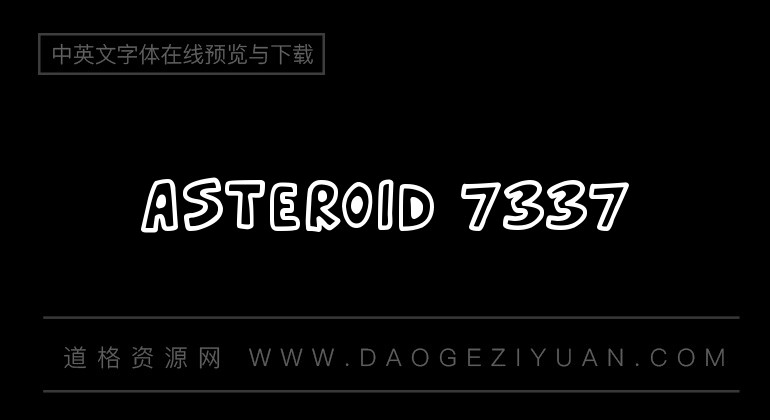
Asteroid 7337是一种现代化的无衬线字体,由Brian Kent设计。它的设计风格融合了科技感和手写字体的特点,配合圆润的线条和有机的形状,使得这种字体看起来既现代又友好。 Asteroid 7337 字体包含了多种字重和斜体字形式,使得它适用于不同大小和风格的设计项目,例如品牌标志、标题、海报、网站等等。该字体的特点包括良好的可读性、干净的设计和通透感。总之,Asteroid 7337 是一种独特的字体,适用于寻求现代感和科技感的设计需求。内容介绍
Asteroid 7337是一款非常不错的手写艺术字体,具有很好的视觉感,适合于文化类的宣传设计、商业类品牌的广告和产品包装设计以及个性化文字排版等较多场景。